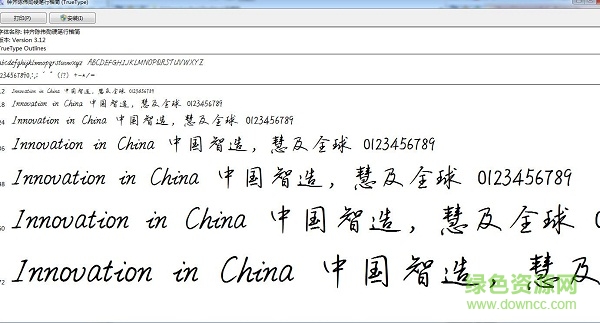
chenwixun jian字體又叫鐘齊陳偉勛硬筆行楷簡字體,該字體線條的起承轉合非常流暢自然,字體角度多變,風格質樸,有著鮮明的識別性,喜歡的朋友歡迎免費下載!
行楷書:是行書與楷書的結合,一般的理解是字中楷多行少,是借鑒行書筆法的楷書,其最大特點是在楷書結構的基礎上融入行書的連帶筆法。變端莊嚴肅為活潑跳動,但基本不作過多的簡省,大致保持楷書風貌。
1.楷書的起筆、行筆、收筆等過程中,提筆、頓筆、轉筆等運用要求嚴格,書寫要平穩(wěn),有輕重提按、入鋒回筆等具體要求。筆數(shù),筆順,一定的行筆規(guī)則是不可以隨意改變的。
2.而行楷的用筆則靈活、方便,一般不需要逆鋒、頓筆、停筆等嚴格的運筆,不強調用筆中更多的提按、筆畫形態(tài),只要求筆道流暢,使轉合理,行筆巧妙。